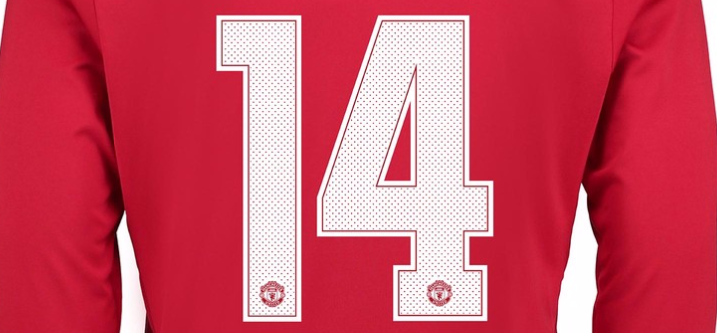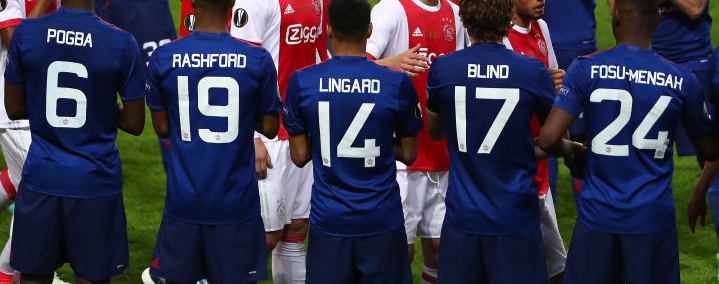
そして、カップ戦で使用するオリジナルのフォントも明らかに(プレミアリーグは統一フォント)。
昨季との違いは歴然だ。下記画像は2016-17シーズンに使用した独自フォント。
丸みを帯びていたフォントから、角ばったものへと変わった。よりオーソドックスな感じだろうか。
背番号は縁取りされており、NFLと似ているという声もあるようだ。